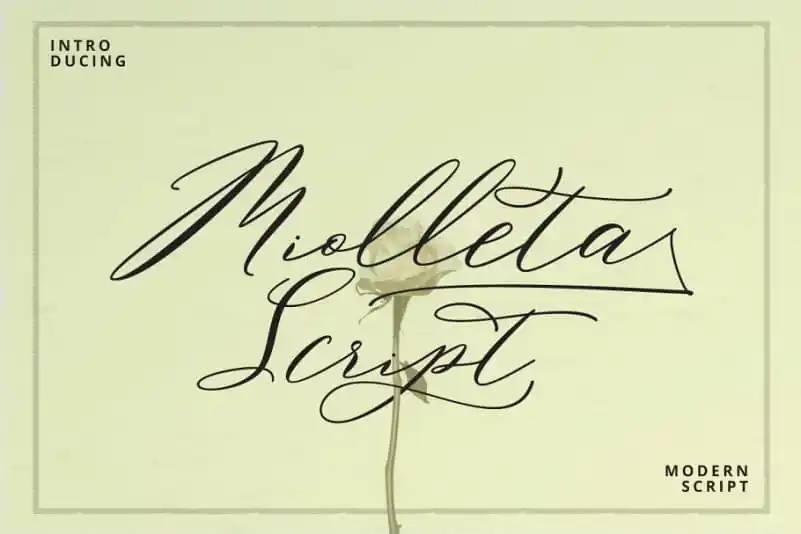
Miolleta Calligraphy Font – Download Grátis
Olha aqui uma descrição envolvente para a Mioletta Calligraphy Font na categoria de Script Fonts: Descubra a arte do chamado modernizado com toques contemporâneos, perfeito para destacar seus projetos digitais. A Mioletta Calligraphy é um marco entre fontes script e chamados. Com seu estilo imperfeito, que se move em ondas como letras dançantes, essa fonte deixa uma impressão leve e limpa. A Mioletta é a fusão única de uma tipografia clássica com elementos modernos. Suas linhas finas e sutis não são perfeitas, mas possuem um delicado equilíbrio que torna o resultado irresistivelmente elegante. Esta fonte é especialmente ótima para aplicar em eventos, cartões de convite ou até mesmo na embalagem de seus produtos. Não importa se você está criando uma identidade visual para sua empresa ou quer dar um toque único a seu site, seja para anúncios de evento ou carteirinhas de entrada, a Mioletta Calligraphy será a escolha perfeita. Com sua versatilidade, você pode usar essa fonte em um vasto leque de aplicações, incluindo nomes de slides, cards de blog personalizados e até mesmo embalagens e cartões de despedida. O que torna a Mioletta Calligraphy tão especial é seu formato ideal para criação de logotipos ou ícones, e quando se trata de criar uma identidade visual única, essa fonte pode fazer toda a diferença. Seja um empreendedor criando um site impecável ou alguém que deseja dar ao seu produto uma cara inigualável, a Mioletta é a escolha perfeita para você. E sem esquecer do mercado de marketing digital, a Mioletta Calligraphy também pode ser usada como fonte para blogs e páginas de redes sociais. Ela tem um visual atraente e moderno que certamente ajudará sua marca a se destacar no ambiente digital frenético em que vivemos.